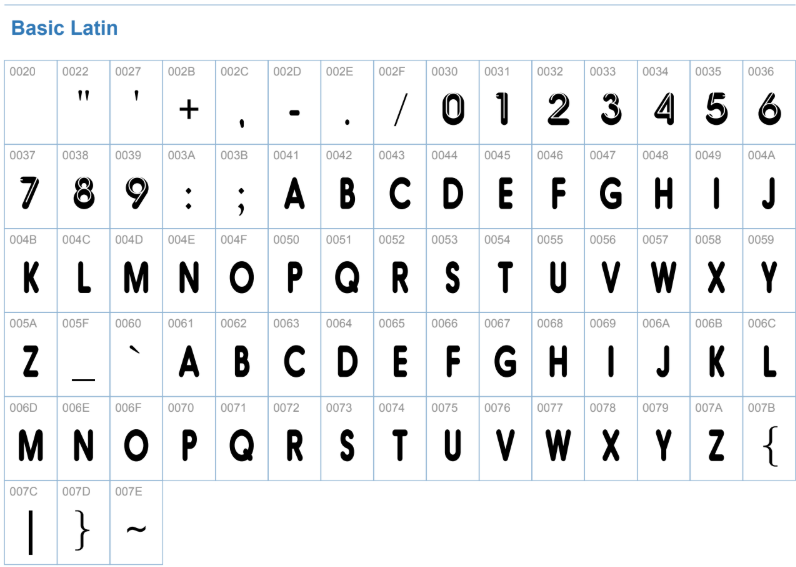
A nova temporada chegou e a Universidad Católica já revelou seu arsenal visual para 2026. Mais do que o design da camisa, o grande protagonista da identidade nos gramados é a tipografia que carrega nome e número nas costas — aquela que a torcida faz questão de ter no manto, no wallpaper e na camisa personalizada.
Se você é colecionador, designer ou um cruzado que respira cada detalhe da Franja, sabe que a fonte oficial conecta tradição, inovação e o peso de San Carlos de Apoquindo. Para facilitar seu projeto, o Fontes Esportivas disponibiliza o arquivo fan-made que reproduz com fidelidade o estilo da temporada, pronto para download.
- Peso da fonte: Regular com outline (contorno) já embutido para simular o efeito da serigrafia
Estilo visual da tipografia
A família tipográfica escolhida para 2026 equilibra modernidade e a identidade clássica da UC. Os números têm construção geométrica com cantos levemente angulados, que remetem à cruz característica do escudo, sem perder a robustez exigida pela TV e pelo estádio. As hastes são grossas e o espaçamento interno é generoso, o que garante leitura instantânea até mesmo em transmissões ruins.
As letras do nome seguem caixa alta padrão com acabamento limpo e sem serifa, mantendo legibilidade máxima sobre o tecido. O contorno externo, presente em todas as opções de camisa, reforça o contraste e impede que os caracteres “sumam” contra listras ou patrocínios. No geral, a fonte projeta força e elegância — exatamente o que se espera de uma equipe copeira.
Aplicação no uniforme
Home (titular): a camisa branca recebe números e letras em azul marinho com contorno branco, gerando um alto contraste clássico que funciona perfeitamente contra o fundo limpo. A fonte mantém total visibilidade mesmo sob iluminação noturna.
Away (reserva): no manto predominantemente azul, a tipografia aparece na cor branca com outline azul escuro, garantindo que cada dígito se destaque sem agredir a harmonia da peça.
Third (terceira): a terceira camisa, tradicionalmente mais ousada, traz um jogo de cores invertido — base vermelha ou dourada com números em branco, mantendo a mesma estrutura da família tipográfica oficial para preservar a unidade da identidade visual.